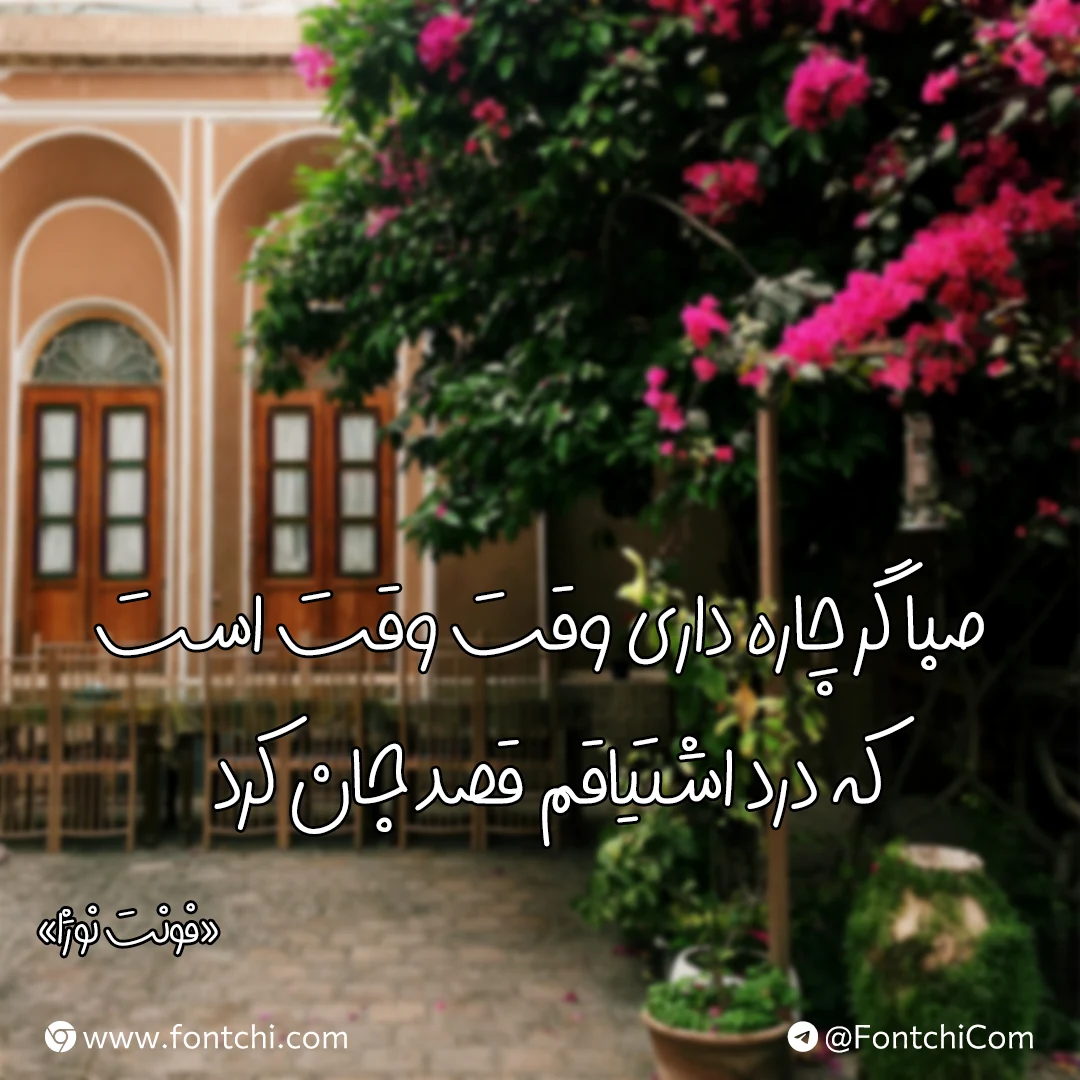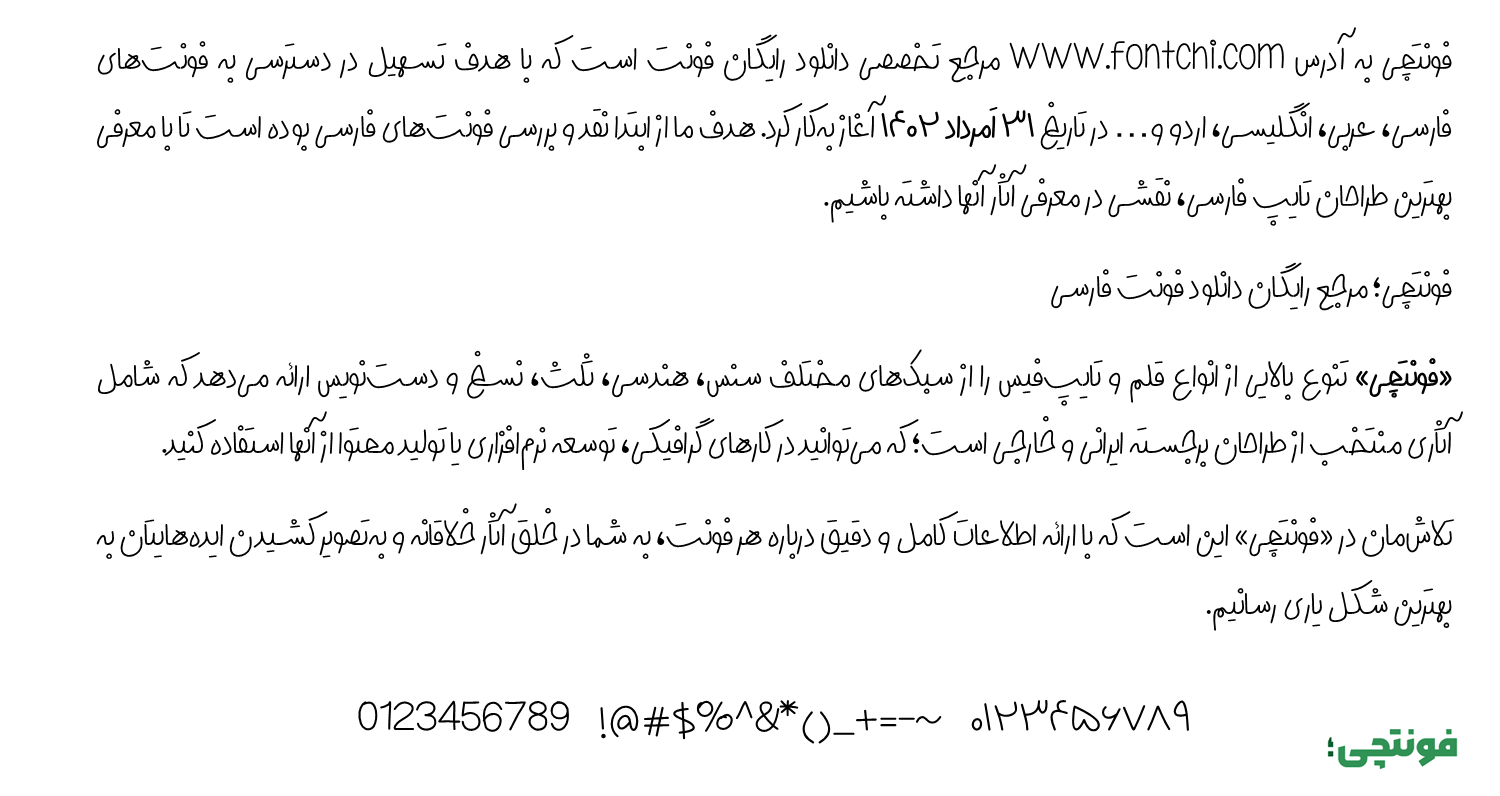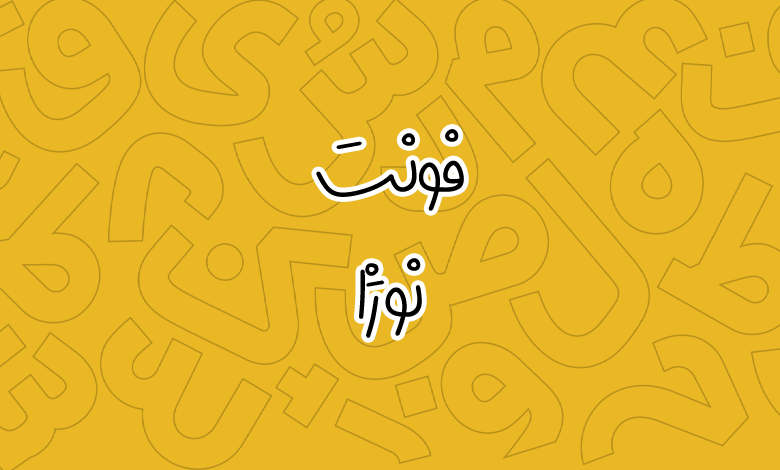
فونت دیجی نوژا (Digi Nozha)
نام نوژا
نام نمایشی Digi Nozha
فونت دیجی نوژا یا فونت نوژا (به انگلیسی: Digi Nozha) از سری فونت دستنویس رایگان است که با الهام از خط بهنوش آذری در یک سبک فانتزی طراحی شده است. این فونت با سبک شاد، پویا و بازیگوش خود در کارهای گرافیکی و تولید محتوا که نیاز به انتقال حس صمیمیت دارید عالی است. نسخه جدیدتر این فونت با نام دیجی نوژا ۲ منتشر شده که ظاهری ضخیم‌تر و دارای حروف جایگزین متنوع است.
فونت فارسی دیجی نوژا توسط مهدی برقگیر از آبان ۱۳۹۹ کار بر روی آن آغاز شده تا اینکه پس از انتشار نسخه‌های اولیه در سال ۱۴۰۲ عرضه رسمی شد. در ادامه با ما همراه باشید تا به نقد و بررسی این فونت کاربردی بپردازیم.
فونت دیجی نوژا دارای شخصیتی فانتزی و پرانرژی است که از زبان‌های فارسی، انگلیسی، کردی و عربی پشتیبانی می‌کند. این فونت با ساختار استاندارد حروف و فاصله‌گذاری مناسب، برای متون کوتاه و بلند مناسب است. همچنین، اعراب‌گذاری هوشمند و هماهنگی بین حروف از ویژگی‌های بارز آن است که باعث می‌شود تایپوگرافی‌های تمیز و حرفه‌ای ایجاد شود.
دیجی نوژا با استایل دست‌نویس و حس فانتزی و مهربانانه‌اش، برای کارهای گرافیکی عاشقانه، کودکانه و خلاقانه بسیار مناسب است. از عکس نوشته در شبکه‌های اجتماعی گرفته تا استفاده برای تامنیل پست‌ها؛ این فونت به‌خوبی حس و حال دست‌خط طبیعی را منتقل می‌کند و برای استوری‌های اینستاگرام و کارت‌پستال‌ها ایده‌آل است. دیگر کاربردهای این فونت:
• پوسترهای تبلیغاتی با ساختار غیر رسمی.
• طراحی جلد کتاب کودکان و نوجوانان یا داستانی.
• طراحی جلد یا محتوای مجلات با موضوعات هنری و ادبی.
این فونت به دلیل هماهنگی با دیگر المان‌های گرافیکی و فونت‌های فارسی و انگلیسی، در پروژه‌های متنوع از جمله طراحی لوگو، پوستر و محتوای دیجیتال به‌خوبی عمل می‌کند. با خوانایی خوبی که دارد می‌توان در متون طولانی نیز از آن استفاده کرد.